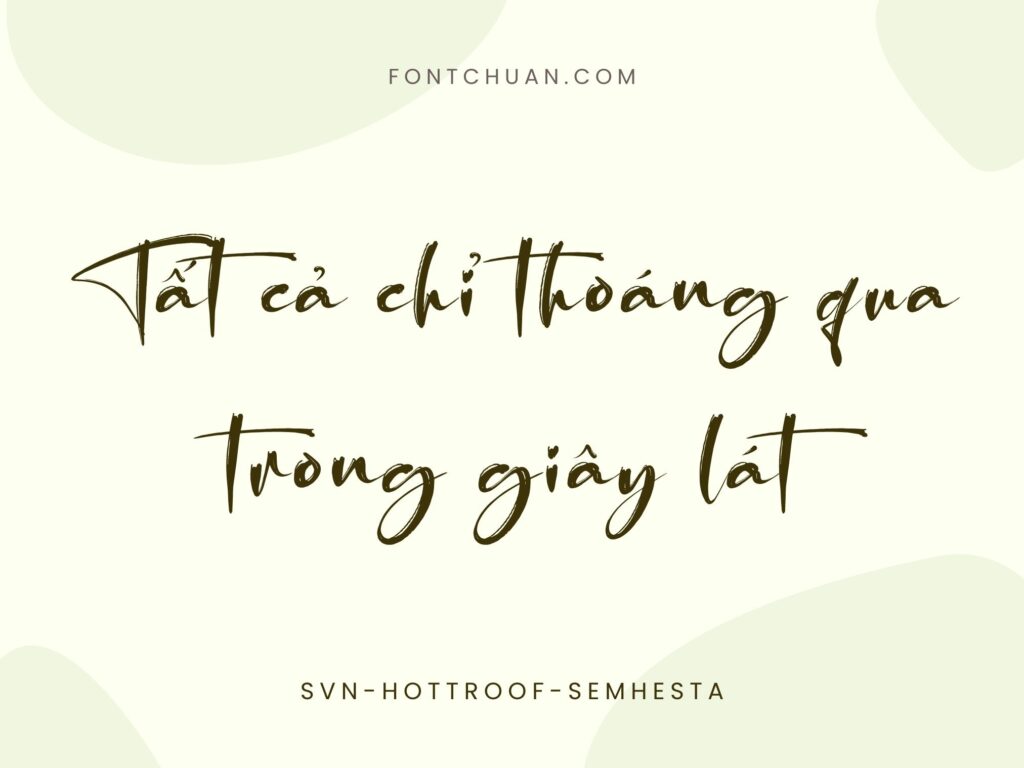
Font SVN Hottroof Semhesta Việt Hóa
Tác giả Font: Pineungtype
Semhesta là một kiểu Font chữ viết tay nhẹ nhàng, được thiết kế bởi Pineungtype và phát hành lần đầu trên Creative Market vào năm 2019. Phiên bản Việt hóa do Styleno.1 Fonts thực hiện đã giúp Semhesta hỗ trợ đầy đủ tiếng Việt cùng với hơn 100 ngôn ngữ khác. Font này được thành viên Font Chuẩn sưu tầm và chọn lọc nhằm mang đến cho cộng đồng một giải pháp chữ viết mềm mại, dễ ứng dụng, đặc biệt phù hợp với các dự án đề cao yếu tố cảm xúc và thẩm mỹ. Bên cạnh đó, Semhesta còn mang hơi hướng của một Font chữ thư pháp hiện đại, tạo nên vẻ tinh tế và sang trọng trong các thiết kế.
Các chữ cái của Semhesta được tạo thành từ những nét viết tay liền mạch, độ dày đều, độ tương phản vừa phải, mang lại cảm giác gần gũi và tự nhiên. Font có tích hợp các ligature giúp dòng chữ trông linh hoạt hơn khi dùng trong tiêu đề, thiệp mời hay chữ ký. Semhesta phù hợp với các ứng dụng thiết kế logo, banner, sản phẩm handmade, bao bì hoặc các chiến dịch quảng bá mang tính cá nhân hóa cao. Những ngành nghề như quảng cáo, spa, ẩm thực và thiệp cưới sẽ tận dụng được nét mềm mại của Semhesta để tạo điểm nhấn trong thiết kế.